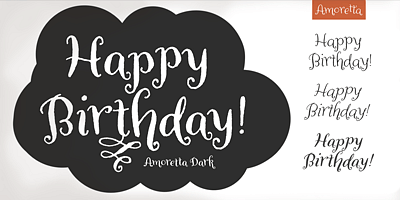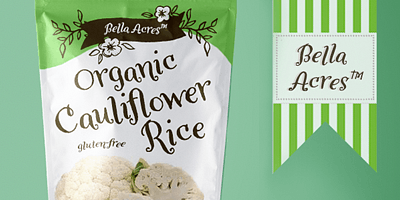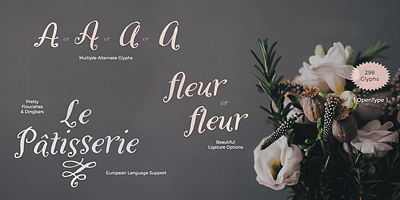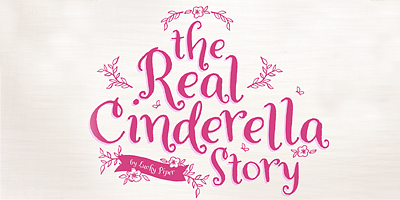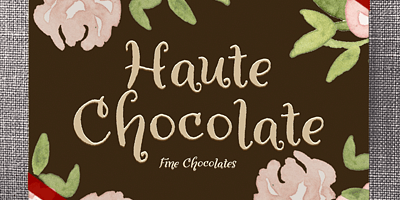
Amoretta est parfaite pour l’impression (image de marque, papeterie, conception de livres, emballage) ou en ligne (eBooks, jeux, applications, sites Web). Facile à lire sur des plateformes à petite ou grande échelle, elle est l’alternative parfaite à un script.